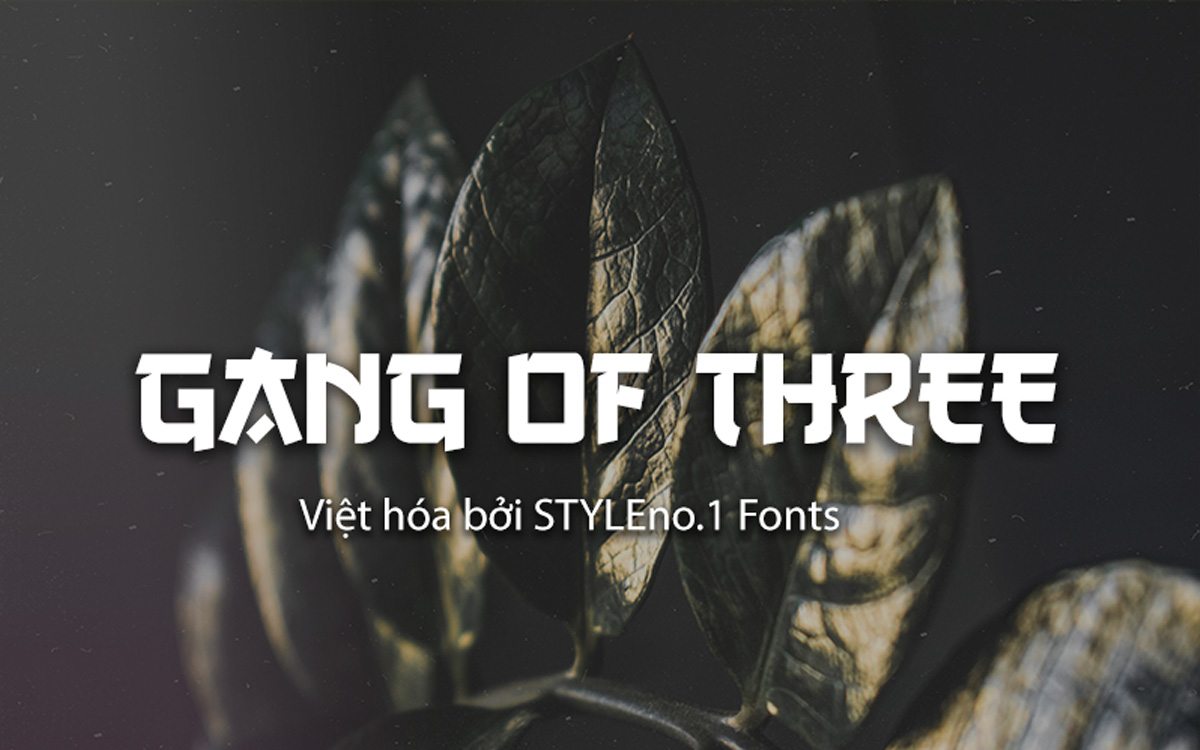
SVN-Gang of Three là font chữ hiện đại sở hữu đường nét cứng cáp, mạnh mẽ và giàu cá tính, đặc biệt phù hợp với các dự án thiết kế liên quan đến thể thao điện tử, game, cơ khí và xây dựng. Với cấu trúc chữ chắc chắn cùng phong cách thị giác nổi bật, font giúp tiêu đề, logo, banner và ấn phẩm truyền thông trở nên chuyên nghiệp, dễ nhận diện hơn ngay từ lần đầu xuất hiện.
Không chỉ tạo cảm giác khỏe khoắn, SVN-Gang of Three còn mang đến tinh thần tốc độ, công nghệ và cạnh tranh. Đây là lựa chọn đáng cân nhắc dành cho nhà thiết kế, đội tuyển eSports, studio game, doanh nghiệp cơ khí, đơn vị xây dựng hoặc bất kỳ thương hiệu nào đang tìm kiếm một kiểu chữ có khả năng truyền tải sự quyết đoán và bền vững.
Font chữ hiện đại cứng cáp SVN-Gang of Three dành cho thể thao điện tử, game, cơ khí và xây dựng
Trong thiết kế thương hiệu, font chữ không chỉ có nhiệm vụ trình bày nội dung mà còn góp phần thể hiện tính cách, định vị và thông điệp của sản phẩm. Một kiểu chữ thanh mảnh thường tạo cảm giác tinh tế, trong khi những đường nét dày, góc cạnh và chắc chắn lại gợi liên tưởng đến sức mạnh, công nghệ, độ bền và tinh thần chinh phục. SVN-Gang of Three được định hình theo hướng đó, giúp các dự án cần phong cách mạnh mẽ xây dựng diện mạo nhất quán và thu hút.
Font chữ hiện đại cứng cáp SVN-Gang of Three phát huy hiệu quả nhất khi được sử dụng ở kích thước lớn như tiêu đề chính, tên thương hiệu, slogan, tên nhân vật, tên đội tuyển hoặc thông điệp quảng cáo ngắn. Kiểu dáng nổi bật giúp nội dung tạo được điểm nhấn rõ ràng trên nhiều nền tảng, từ màn hình kỹ thuật số đến các sản phẩm in ấn. Người dùng có thể kết hợp font với màu sắc tương phản, hiệu ứng kim loại, ánh sáng neon hoặc họa tiết công nghiệp để tăng thêm chiều sâu cho thiết kế.
Kiểu dáng mạnh mẽ, hiện đại và giàu khả năng nhận diện
Điểm nổi bật của SVN-Gang of Three nằm ở diện mạo khỏe khoắn, rõ khối và có cá tính thị giác mạnh. Các đường nét cứng cáp giúp nội dung trở nên dứt khoát, tạo cảm giác ổn định và đáng tin cậy. Phong cách này phù hợp với những thương hiệu muốn nhấn mạnh tinh thần cạnh tranh, khả năng vận hành, sức bền hoặc tính chuyên nghiệp trong môi trường công nghệ hiện đại.
Khi xuất hiện trên poster, banner hoặc trang bìa, font có thể nhanh chóng thu hút ánh nhìn và tạo thứ bậc thông tin rõ ràng. Nhà thiết kế có thể dùng SVN-Gang of Three cho tiêu đề lớn, sau đó kết hợp cùng một font sans serif đơn giản ở phần nội dung để bảo đảm khả năng đọc. Sự tương phản giữa kiểu chữ cá tính và phần văn bản trung tính sẽ giúp bố cục vừa nổi bật, vừa cân bằng.
Phù hợp với thiết kế thể thao điện tử và nhận diện đội tuyển eSports
Thể thao điện tử đòi hỏi một ngôn ngữ hình ảnh có tốc độ, năng lượng và khả năng tạo dấu ấn mạnh. SVN-Gang of Three đáp ứng tốt yêu cầu này nhờ phong cách chữ quyết đoán, thích hợp để thể hiện tên đội tuyển, tên giải đấu, khẩu hiệu thi đấu hoặc nội dung quảng bá sự kiện. Font có thể được ứng dụng trên nhiều hạng mục truyền thông eSports như:
- Logo chữ và bộ nhận diện dành cho đội tuyển thể thao điện tử.
- Poster giải đấu, lịch thi đấu và bảng thông báo kết quả.
- Ảnh bìa, ảnh đại diện và nội dung truyền thông trên mạng xã hội.
- Áo đấu, huy hiệu, cờ cổ vũ và các sản phẩm lưu niệm.
- Thumbnail video, giao diện livestream và lớp đồ họa hiển thị trên màn hình.
Để tăng hiệu quả thị giác, người dùng có thể phối font với các gam màu giàu năng lượng như đỏ, cam, xanh điện hoặc vàng. Hiệu ứng viền, đổ bóng, chuyển màu và ánh sáng cũng có thể được áp dụng có chọn lọc nhằm tạo cảm giác chuyển động. Tuy nhiên, thiết kế nên giữ khoảng cách chữ hợp lý và hạn chế sử dụng quá nhiều hiệu ứng cùng lúc để tên đội hoặc thông điệp chính luôn rõ ràng.
Tạo điểm nhấn nổi bật cho dự án game và nội dung giải trí số
SVN-Gang of Three là lựa chọn phù hợp cho nhiều dự án game cần một kiểu chữ mạnh, hiện đại và dễ ghi nhớ. Font có thể xuất hiện trên tiêu đề trò chơi, màn hình mở đầu, hình ảnh quảng bá, nội dung giới thiệu bản cập nhật hoặc các nút điều hướng quan trọng. Tùy cách xử lý màu sắc và hiệu ứng, kiểu chữ có thể hỗ trợ nhiều bối cảnh như hành động, chiến thuật, đua xe, khoa học viễn tưởng hoặc phiêu lưu.
Đối với hoạt động sáng tạo nội dung, font cũng có thể được dùng để thiết kế thumbnail cho video đánh giá game, hướng dẫn chơi, tin tức giải đấu hoặc nội dung phát trực tiếp. Hình dáng chữ có sức nặng giúp tiêu đề giữ được sự nổi bật ngay cả khi đặt trên hình nền có nhiều chi tiết. Đây là yếu tố quan trọng trên các nền tảng nơi người xem thường chỉ dành vài giây để quyết định có nhấp vào nội dung hay không.
Khi ứng dụng SVN-Gang of Three trong giao diện game, nhà thiết kế nên ưu tiên các đoạn chữ ngắn và kích thước đủ lớn. Những nội dung dài như mô tả nhiệm vụ, hội thoại hoặc điều khoản sử dụng nên được trình bày bằng font có cấu trúc đơn giản hơn. Cách phân chia này giúp duy trì cá tính của sản phẩm mà không làm giảm trải nghiệm đọc của người chơi.
Thể hiện độ bền và tính chuyên nghiệp trong ngành cơ khí, công nghiệp
Trong lĩnh vực cơ khí và công nghiệp, hình ảnh thương hiệu thường gắn với độ chính xác, hiệu suất, công nghệ và khả năng vận hành bền bỉ. Những đặc điểm cứng cáp của SVN-Gang of Three có thể hỗ trợ truyền tải các giá trị đó một cách trực quan. Font thích hợp để sử dụng cho tên doanh nghiệp, tiêu đề catalogue, biển hiệu xưởng, bao bì thiết bị, nhãn sản phẩm hoặc nội dung quảng cáo máy móc.
SVN-Gang of Three cũng có thể kết hợp hiệu quả với bảng màu công nghiệp gồm đen, xám thép, bạc, xanh đậm hoặc vàng cảnh báo. Khi được đặt cạnh các họa tiết như bề mặt kim loại, lưới kỹ thuật, đường cắt hoặc mô hình máy móc, font góp phần tạo nên tổng thể đồng nhất và chuyên nghiệp. Tuy nhiên, doanh nghiệp nên xây dựng quy chuẩn sử dụng rõ ràng về kích thước, màu sắc và khoảng cách để bảo đảm nhận diện nhất quán trên mọi ấn phẩm.
Ứng dụng linh hoạt cho thương hiệu xây dựng và truyền thông dự án
Lĩnh vực xây dựng cần thể hiện sự vững chắc, an toàn và đáng tin cậy. Với hình thức chữ mạnh và có trọng lượng thị giác, SVN-Gang of Three có thể được ứng dụng cho logo chữ, slogan, biển quảng cáo công trình, hồ sơ giới thiệu năng lực hoặc nội dung truyền thông bất động sản. Font giúp các thông điệp như “bền vững”, “kiến tạo”, “chất lượng” và “đúng tiến độ” được nhấn mạnh bằng một diện mạo phù hợp.
Trong các chiến dịch quảng bá dự án, SVN-Gang of Three có thể đảm nhiệm vai trò font tiêu đề trên pano, brochure, banner website và bài đăng mạng xã hội. Để có một bố cục hiệu quả, người thiết kế có thể thực hiện theo các bước:
- Sử dụng SVN-Gang of Three cho tên dự án hoặc thông điệp chính.
- Kết hợp với font dễ đọc hơn cho mô tả, thông số và thông tin liên hệ.
- Ưu tiên màu tương phản để tiêu đề nổi bật trên hình ảnh công trình.
- Kiểm tra khả năng hiển thị trên cả màn hình nhỏ và sản phẩm in khổ lớn.
- Thống nhất cách sử dụng font trong toàn bộ hệ thống nhận diện thương hiệu.
SVN-Gang of Three là giải pháp đáng chú ý dành cho những dự án cần một font chữ hiện đại cứng cáp, có cá tính và khả năng tạo điểm nhấn mạnh. Từ thể thao điện tử, game đến cơ khí và xây dựng, kiểu chữ này có thể hỗ trợ thương hiệu thể hiện tinh thần cạnh tranh, công nghệ, độ bền và sự chuyên nghiệp trên nhiều loại ấn phẩm.